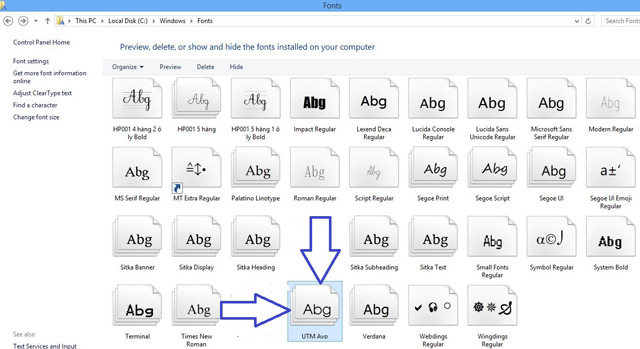
Bộ font chữ lớp 1 soạn bài giảng điện tử
Trong bộ font chữ viết tay dành cho học sinh lớp 1 mà chúng tôi chia sẻ sau đây sẽ có 2 loại font chữ.
- 1 là các loại font chữ ô ly để thiết kế các file tập viết cho học sinh lớp 1.
- 2 là các loại font chữ in hoa để sử dụng khi soạn giáo án điện tử PPt.